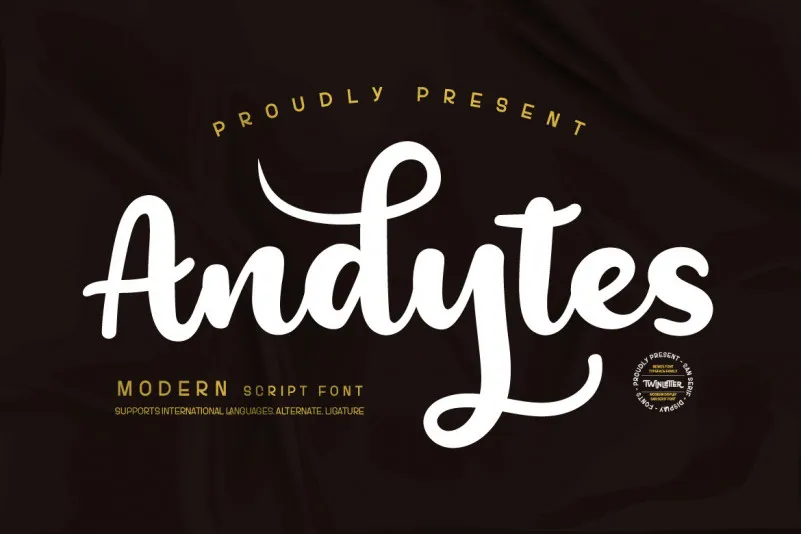
Andesytes Font – Fonte Grátis
Andesytes Font
Esta é uma fonte de letra tipográfica criada para atentar a cada desenho anatómico da letra, proporcionando um resultado limpo e elegante quando usada. A própria fonte foi projetada com toques naturais do próprio punho, oferecendo recursos alternativos, ligaturas e suporte multi-língua. Twinletter é o designer responsável por essa arteful criação de fontes que reflete não apenas a forma da letra, mas também sua essência única. Ideal para quem busca uma combinação perfeita entre elegância e personalidade nas suas criações gráficas. Descubra como Andesytes Font pode tornar sua tipografia ainda mais especial com seus detalhes meticulosamente cuidados.